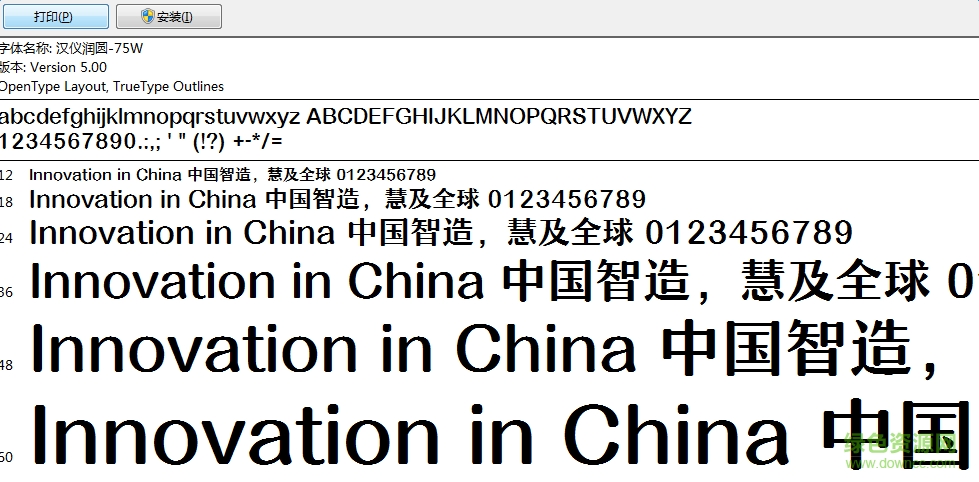
hyrunyuan gew(儀潤(rùn)圓 75w)字體是一款圓潤(rùn)飽滿的中文圓體字體,線條簡(jiǎn)潔,字形清晰,可用于招牌、包裝設(shè)計(jì)、廣告等商業(yè)字體!喜歡這款字體朋友歡迎在綠色資源網(wǎng)免費(fèi)下載!
漢儀潤(rùn)圓的創(chuàng)作源于在圓體的基礎(chǔ)上,加入黑體,宋體的元素特征創(chuàng)新而成,力求打造一款穩(wěn)重大氣輕松優(yōu)雅的家族字體。筆畫(huà)設(shè)計(jì)融入隸書(shū)的書(shū)寫(xiě)味道,并將筆畫(huà)橫豎比例拉開(kāi),宋體的筆畫(huà)特征令字體更輕松,避免笨拙的視覺(jué)效果。